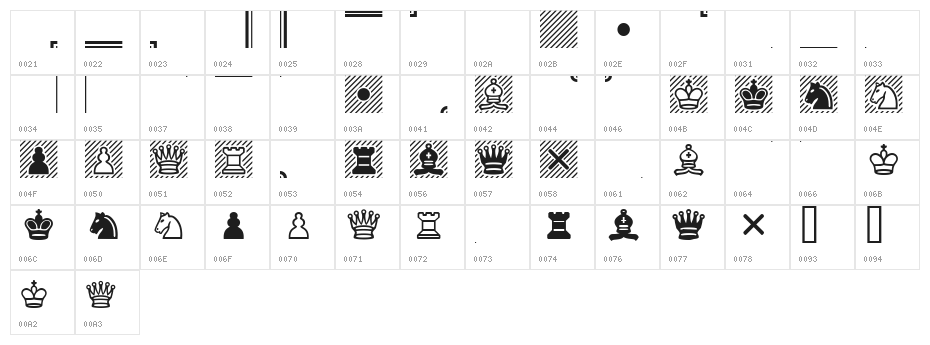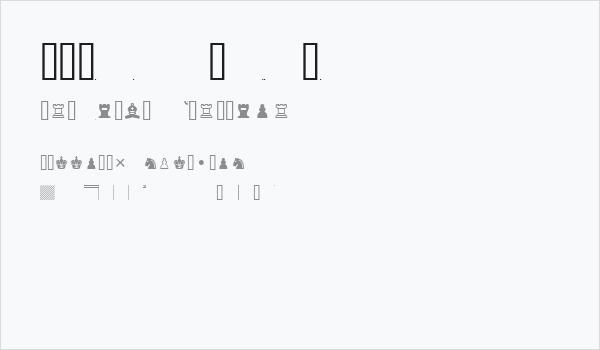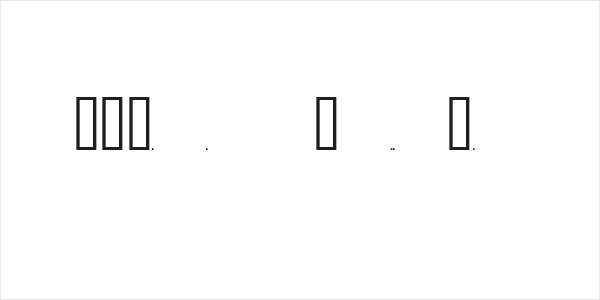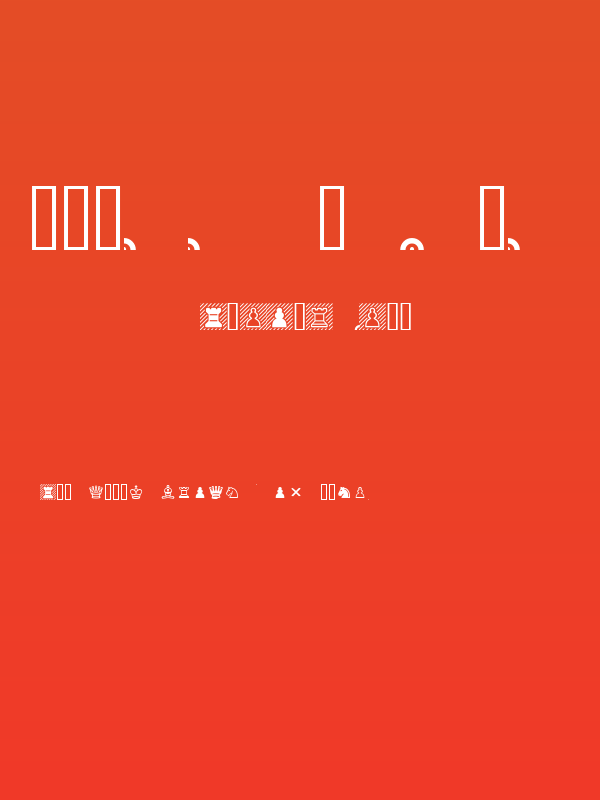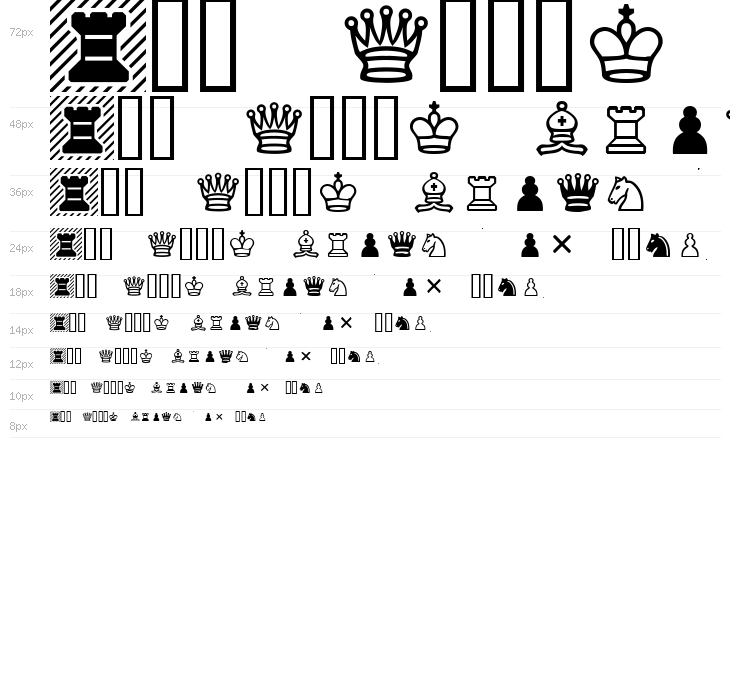
Chess Cases Font
| 使用场景 | Decorative elements for chess-themed projects. |
| 推荐项目 | This set could be used for chess-related designs or educational materials about chess. |